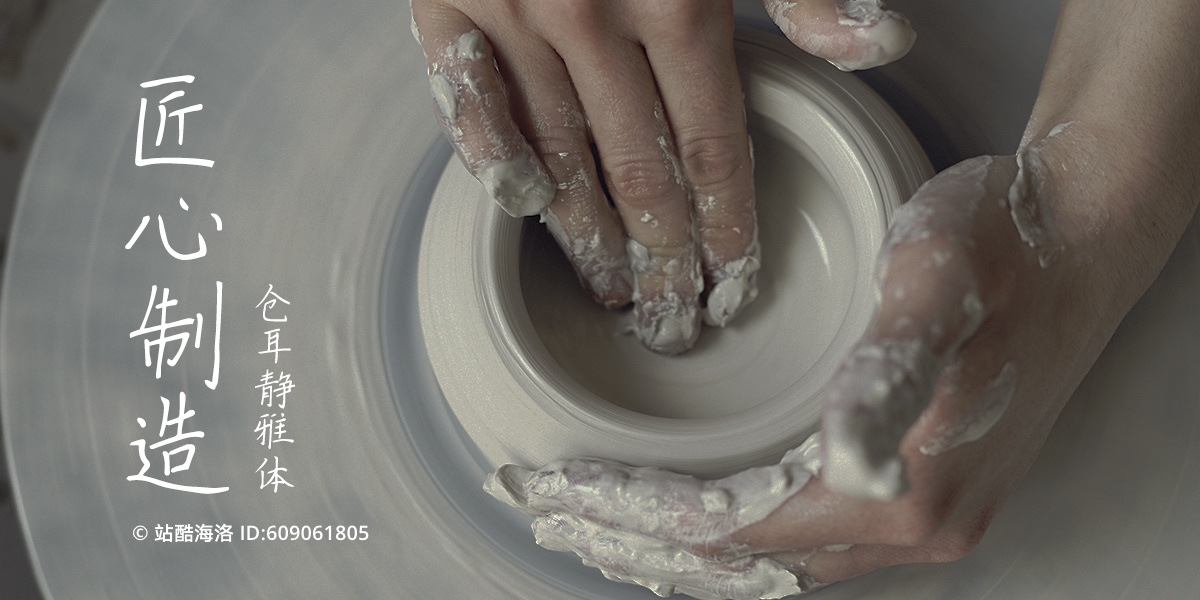
仓耳静雅体
仓耳静雅体,这款手写字体楷法严谨,放而不流,拘而不拙,结字方圆,笔法肥劲,书法性极强。不仅有书法的美感,还兼顾易读易识别的实用特性。 字体的整体结构偏于颜体字,探源篆隶,书写上更加自然流畅,将字体的书法之感表现的淋漓尽致。是一款适合产品包装、社交网络、屏幕阅读的个性化用字。
仓耳静雅体字体介绍